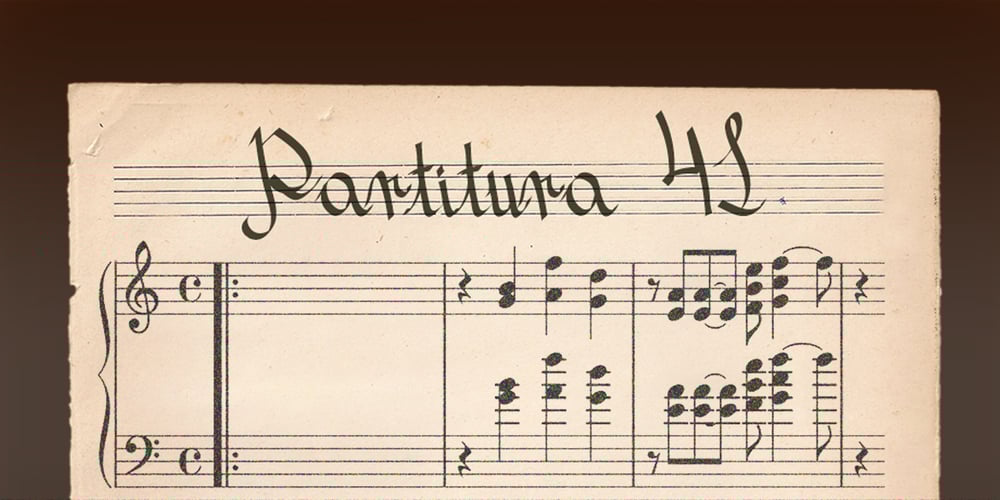
Partitura1941
Partitura1941 font
Partitura1941 Font Family was designed by Idoia de Luxan and published by Idoia de Luxan. Partitura1941 contains 1 styles and family package options. Tipograf�a caligr�fica inspirada nos t�tulos das canci�ns dun caderno familiar de partituras de 1941. � unha fonte creada da maneira m�is fidel posible a como se debuxar�a cunha pluma estilogr�fica do momento. Axeitada para t�tulos ou letras capitais. Non se recomenda empregar para textos longos, de non ser que se pretenda simular un arquivo antigo dun estilo manuscrito semellante. Tipograf�a caligr�fica inspirada en los t�tulos de las canciones de un cuaderno familiar de partituras de 1941. Es una fuente creada de la manera m�s fiel posible a como se dibujar�a con una pluma estilogr�fica del momento. Adecuada para t�tulos o letras capitales. No se recomienda utilizar pata textos largos, a no ser que se pretenda simular un archivo antiguo de un estilo manuscrito semejante.Calligraphic typography inspired by the titles of the songs of a family notebook of 1941. It is a source created in the most faithful way possible to how it would be drawn with a stylus pen of that moment. Suitable for titles or capital letters. It is not recommended to use for long text, unless you pretend to simulate an old archive with a similar manuscript style.